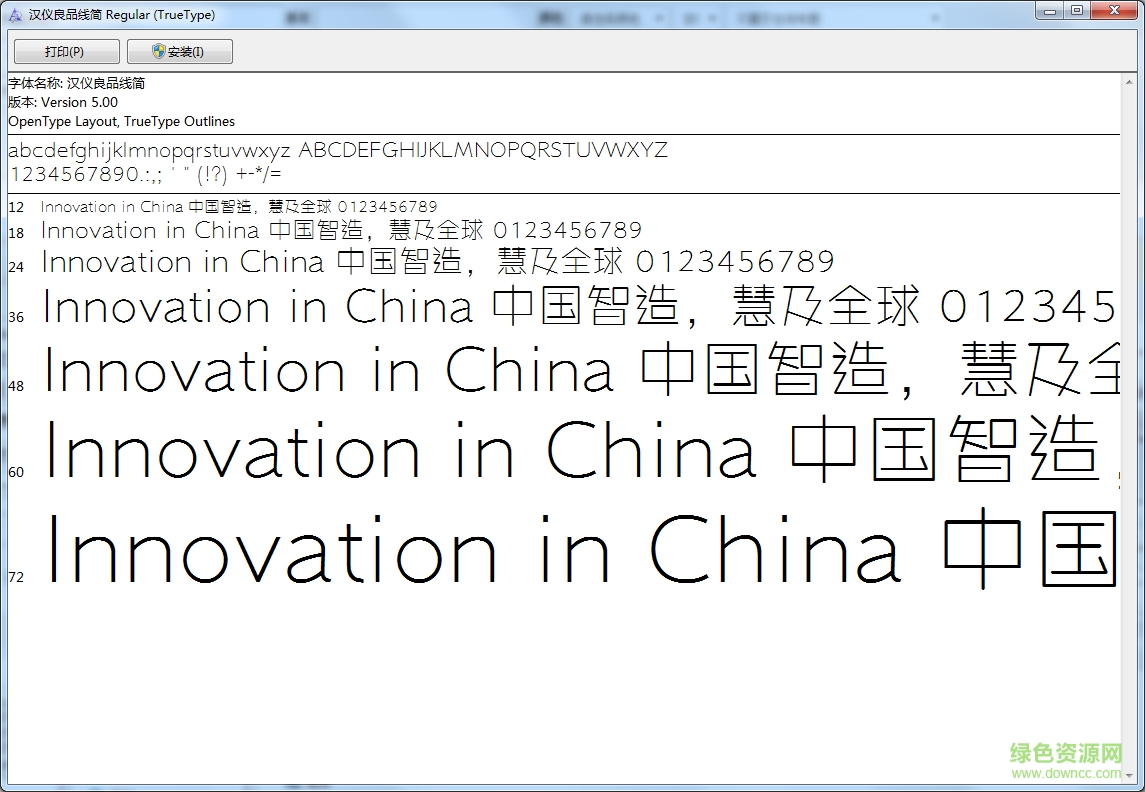
漢儀良品線字體是一款非常好用的簡(jiǎn)體漢儀字體,字體整體感覺簡(jiǎn)約優(yōu)雅,支持中文、英文和阿拉伯?dāng)?shù)字,適合廣告和商務(wù)使用,喜愛的朋友趕快到綠色資源網(wǎng)下載使用吧!
官方介紹
這款字體清新規(guī)整,充滿簡(jiǎn)約的設(shè)計(jì)感,重心偏低穩(wěn)定性高,筆畫由直線組成,線條簡(jiǎn)單靈動(dòng),使人感覺優(yōu)雅有品質(zhì)。在圓體的基礎(chǔ)上加入大膽的改變調(diào)整,使得整套字更有現(xiàn)代感。適合畫冊(cè)標(biāo)題、海報(bào)設(shè)計(jì)、廣告宣傳等場(chǎng)合使用。